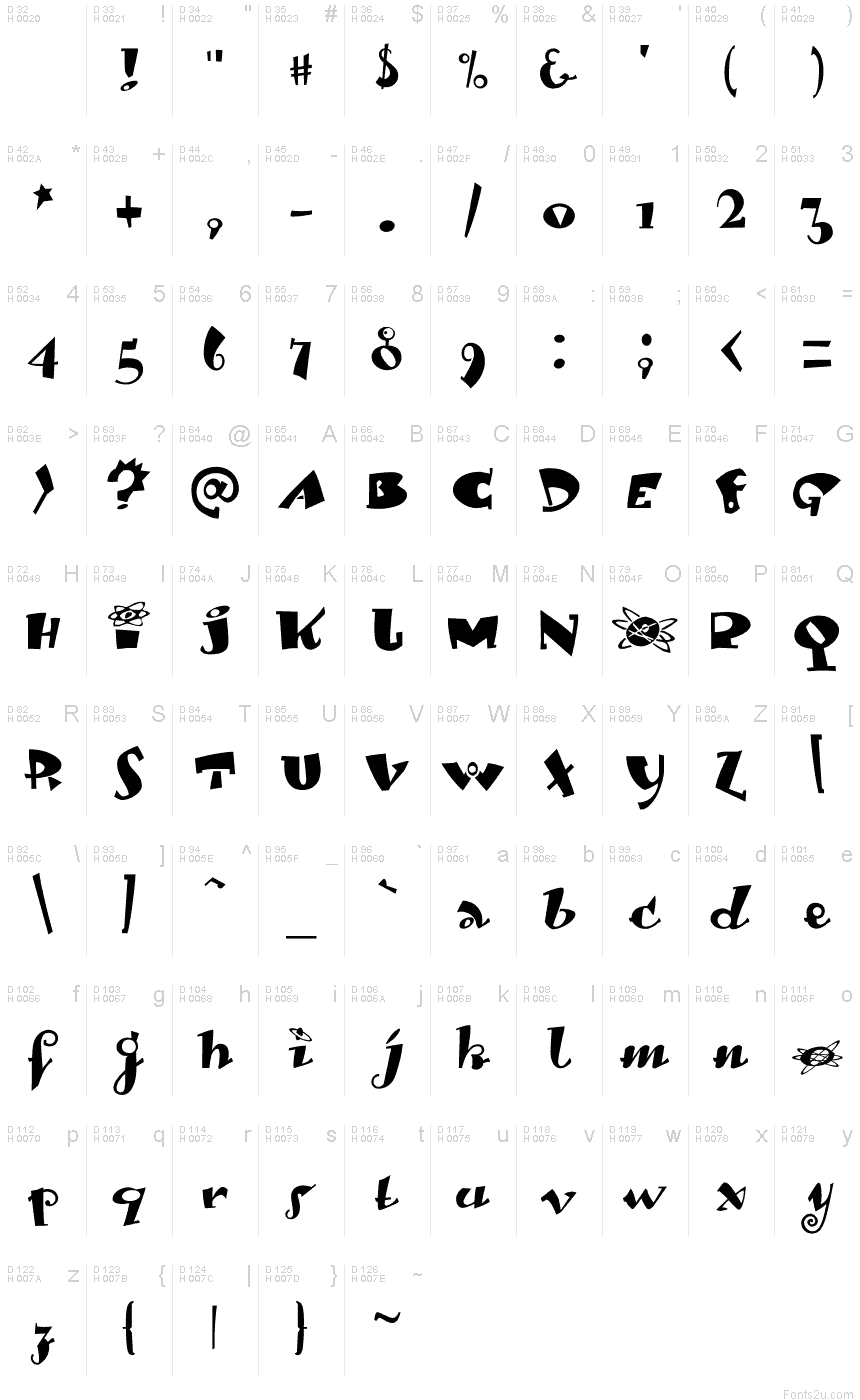
LambadaDexter-Medium
Lambada Dexter autorstwa Francoisa Bruela to darmowy krój typu comic display o płynnym, odręcznym rytmie oraz zaokrąglonych, nieregularnych krzywiznach, które nadają mu żywy, szkicowy charakter. Litery są blisko siebie, z płynnymi łączeniami, miękkimi krzywiznami i kilkoma nagłymi zwrotami, dzięki czemu cały napis nie sprawia wrażenia mechanicznego.
Ten darmowy font świetnie sprawdza się na plakatach, ulotkach, w brandingu dla dzieci, jako akcent w logotypach oraz w krótkich grafikach do mediów społecznościowych, gdzie odręczny, nieformalny styl pozwala skutecznie przekazać komunikat. Pasuje również do zabawnych opakowań, tytułów komiksowych i niezobowiązujących gadżetów, ponieważ jego kształty są wyraziste, a jednocześnie zachowują czytelną strukturę.